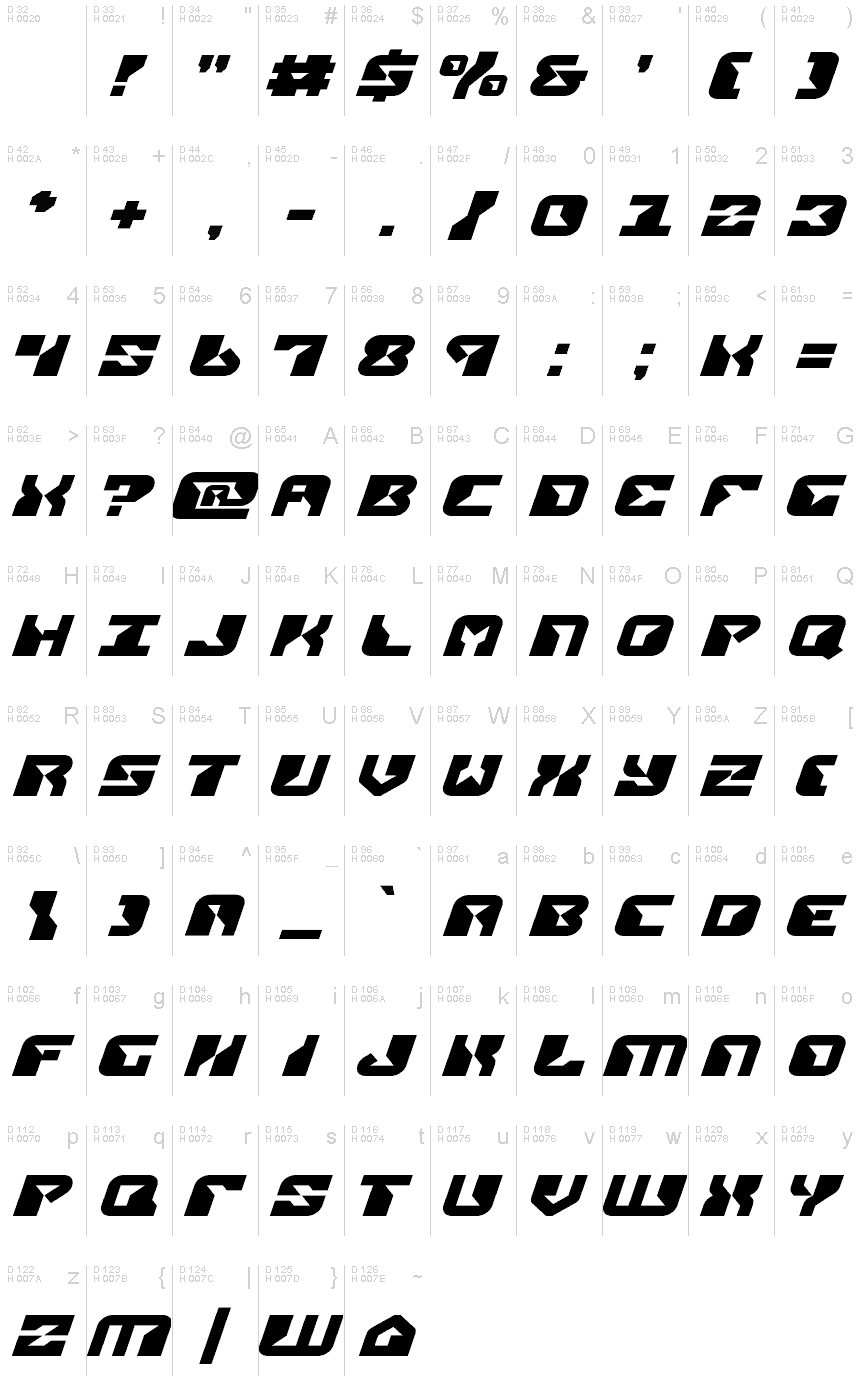
Replicant Expanded Italic od Iconian Fonts to darmowy, futurystyczny krój displayowy z ostrym, sci-fi zacięciem i technicznym, „maszynowym” charakterem. Litery są szerokie, ciężkie i pocięte kanciastymi wycięciami oraz klinowatymi otworami, co nadaje wielkim literom szybki, syntetyczny rytm, całkowicie odmienny od gładkiej kursywy.
Najlepiej sprawdza się tam, gdzie chcesz od razu wywołać wrażenie bliskiej przyszłości: w logotypach gier, tytułach filmowych, plakatach technologicznych, okładkach płyt i nagłówkach marek. Jako darmowy font, świetnie radzi sobie w krótkich tekstach i logotypach, ponieważ szerokie formy i powtarzające się ukośne cięcia sprawiają, że nawet kilka liter wygląda na zaprojektowane przez inżyniera.